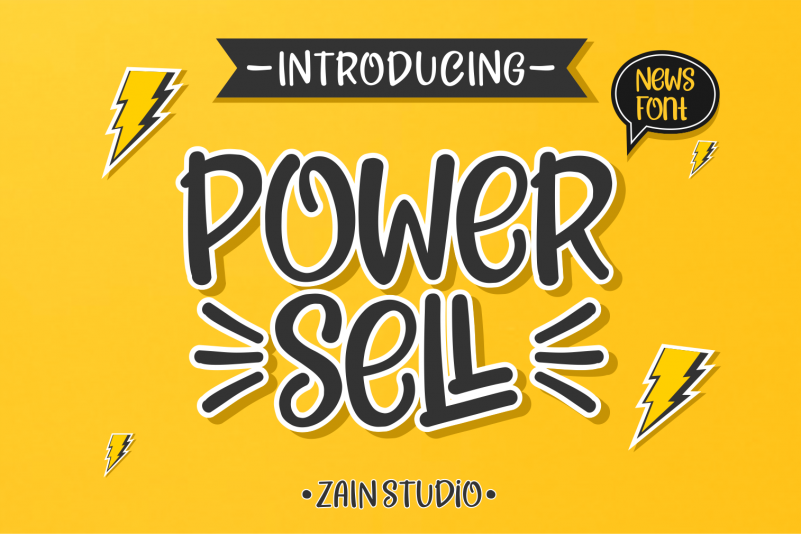
Power Sell – Fun Font – Download Grátis
Aqui está uma breve descrição natural e envolvente para a página de download da font PowerSell – Fun Font: PowerSell é uma fonte display vibrante e descontraída que combina elementos de escrita manuscrita, criando um charme único e personalizado. Ideal para designers gráficos, especialmente aqueles que trabalham com máquinas de corte como o Cricut ou Silhouette, essa fonte é ultra suave, otimizando a precisão do seu trabalho. Com uma estética animada e dinâmica, PowerSell é perfeitamente adaptável para criar títulos em livros infantis, scrapbooking, logotipos, ícones, frases ou citações para cartões de felicitações (inclusive datas como Halloween e Ano Novo). Ela também se destaca no Instagram, Facebook e outros canais digitais, tornando-a ideal não apenas para criar conteúdo personalizado, mas também para adicionar uma pitada de criatividade aos seus posts nas redes sociais. Esta fonte é perfeita tanto para designers iniciantes quanto para profissionais, graças ao seu design intuitivo e à sua facilidade na criação de designs atraentes. Se você está buscando um recurso gráfico que enriqueça suas produções digitais e físicas com uma personalidade única e vibrante, PowerSell é o seu fonte ideal.